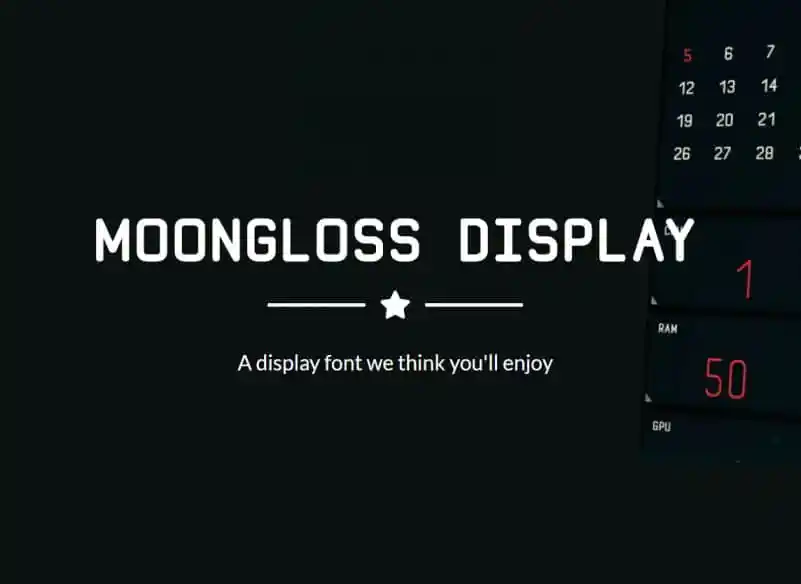
Introduzimos a Moongloss Sans Font Family para ajudar na sua jornada criativa. Esta font foi projetada para ambientes expositivos, tornando-a perfeita para exibir datas, horas ou pequenos pedaços de informação. Embora haja muitas outras fontes disponíveis que atendem a esses fins, nenhuma é como esta: com um design cuidadosamente concebido e compartilhado pelo designer Immanuel Smith. A Moongloss Sans é uma família multi-estilo de tipo seríssimo em caixa alta, projetada para se adaptar a uma ampla variedade de trabalhos, desde designs de logotipos até convites de casamento, postagens no Facebook ou Instagram e muito mais. É um luxo ter uma fonte tão elegante e versátil na sua coleção.